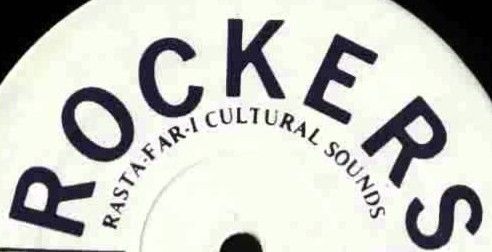
Alguien puede identificar las dos tipografías usadas en este logo?
Este logo aparece en la galleta de un disco de finales de los años 70, por si ayuda...
La de abajo sí que parece Garamond. No exactamente igual, pero muy parecida...
La linea de arriba con la DIN Medium no la veo tanto, hay mucha diferencia con la S y la E, sobretodo.
Se parece también a una fuente básica que se llama Trebuchet, pero tampoco es...
A ver si doy con ella.
La de abajo parece Adobe Garamond Bold o similar y la de arriba, si no necesitas que sea exactamente la misma puedes sustituirla por DIN Medium, es parecida.